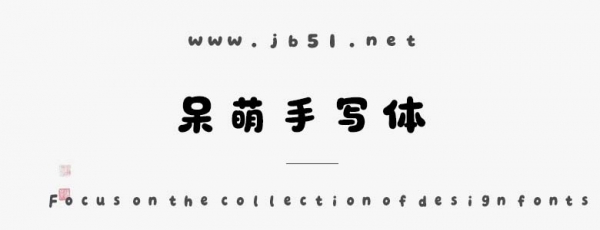
呆萌手寫體是一款不錯的藝術字體,基于SIL Open Font License 1.1協(xié)議【永久開源】的中文手寫字體,具有很好的視覺感,適合應用于藝術設計、平面宣傳設計、網頁設計,書法字帖等領域,需要的朋友可以前來本站下載。
當前Version 1.00版本收錄常用漢字及基礎符號,滿足商業(yè)設計、文創(chuàng)產品、網絡傳播等多場景應用需求,后續(xù)版本按需迭代更新。
這款字體保留自然書寫的溫度感:圓潤造型與稚拙的筆劃結構相映成趣,通過靈動的連筆轉折與適度的墨跡留痕,營造出充滿童真的視覺韻律。每個字符曲線Q彈,既保持文字識別性,又賦予版面獨特的治愈系氛圍。